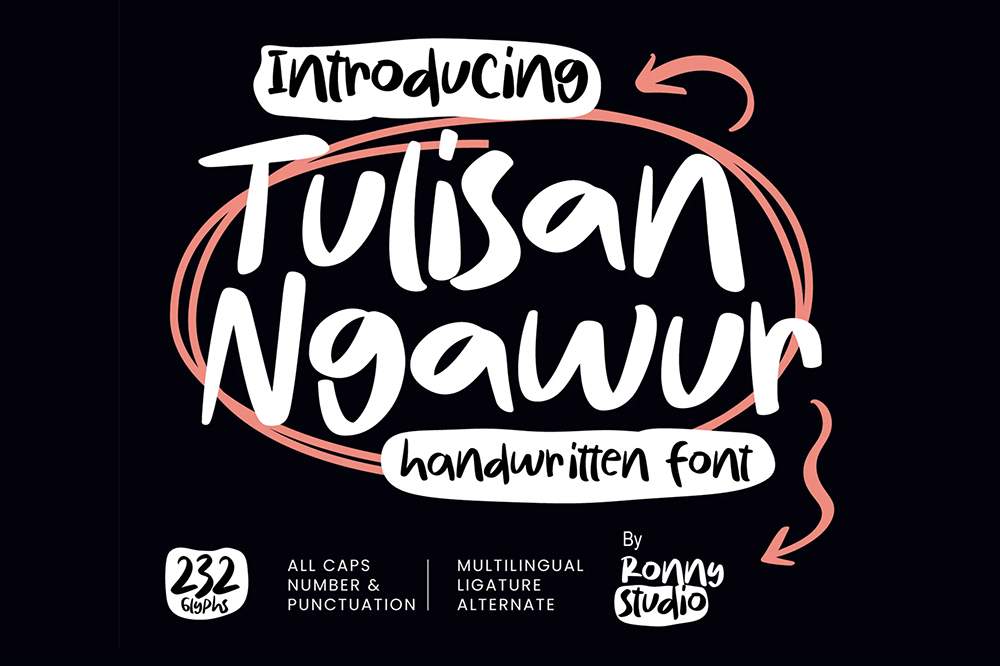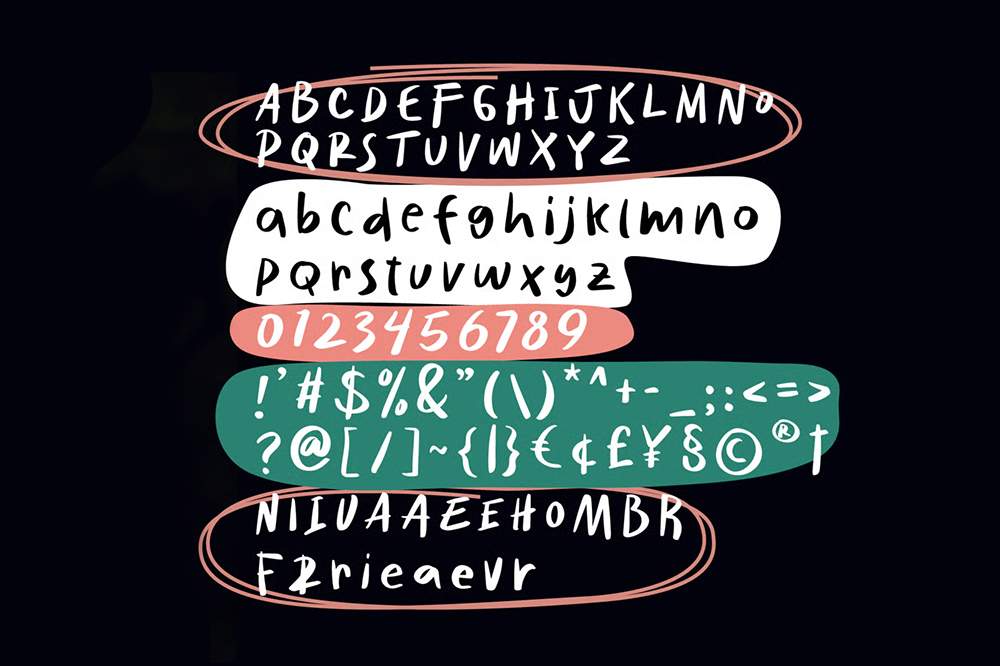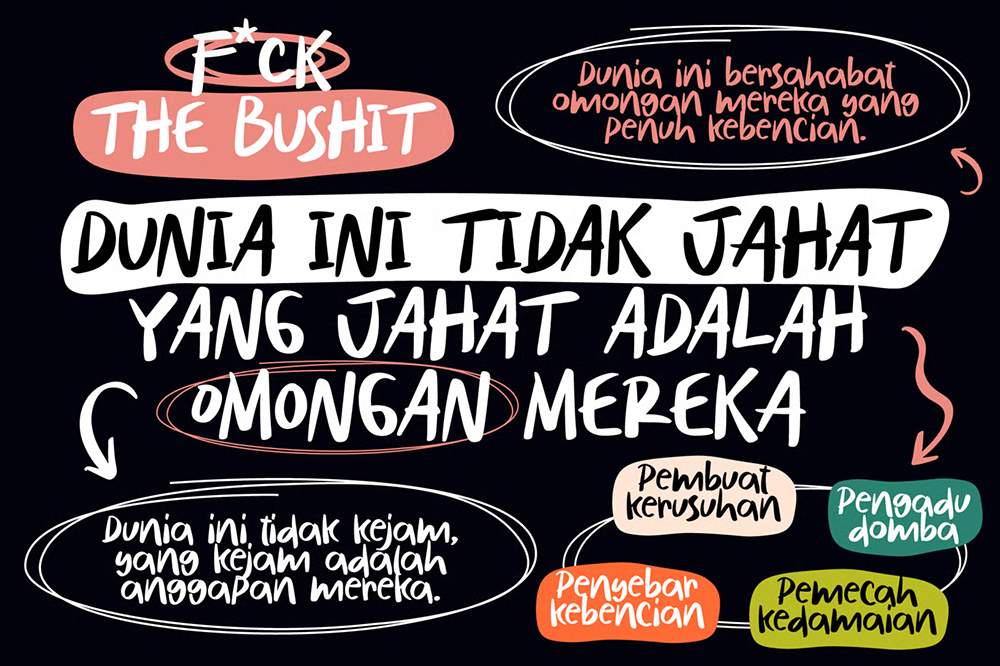
دانلود فونت انگلیسی Tulisan Ngawur Font
فونت پرمیوم و انگلیسی Tulisan Ngawur Font يک فونت دستنويس منحصر به فرد با سبکی غيررسمی و سرشار از شخصيت است! اين فونت به گونهای طراحی شده است که به هر طرحی حس آرامش، خلاقيت و کمی “عجيب و غريب” بدهد. مناسب برای پروژههايی که نياز به چاپ سرگرمکننده، سرزنده و آماده برای استفاده دارند، مانند طراحی پوستر، کالا، رسانههای اجتماعی يا ساير پروژههای خلاقانه و…
مزایای استفاده از فونت لاتین Tulisan Ngawur چیست؟